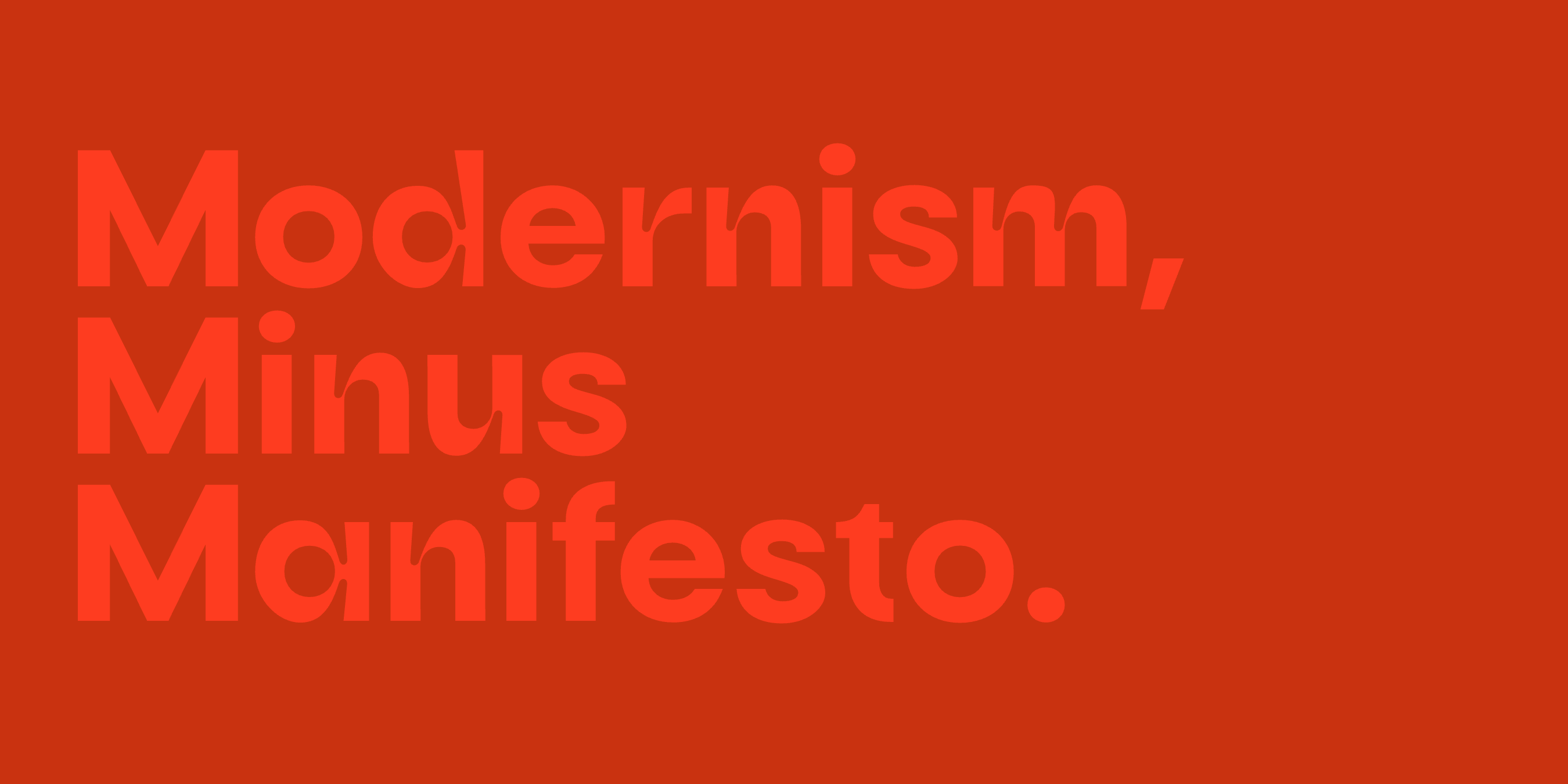
Moderne Typografie: Was sie 2026 wirklich bedeutet
Moderne Typografie ist einer dieser Begriffe, unter denen jeder Designer etwas anderes versteht. Für die einen sind es geometrische Sans-Serifs in Schweizer Tradition. Für andere die kontrastreichen Didonen aus Modemagazinen. Für wieder andere alles, was in den letzten zwölf Monaten erschienen ist. Nichts davon ist falsch, aber nichts davon ist vollständig.
Was Designer 2026 meist mit „modern“ meinen, ist Schrift, die in allen Kontexten funktioniert, in denen Marken heute bestehen müssen. Verpackungen, die für Instagram fotografiert werden, Produktseiten, durch die man auf dem Handy scrollt, Plakatwände, die man mit 100 km/h passiert, App-Oberflächen, auf die man eine halbe Sekunde schaut. Die Formen, die an all diesen Orten funktionieren, haben einige Merkmale gemeinsam.
Wie moderne Typografie in der Praxis aussieht
Erstens sind moderne Schriften auch in kleinen Größen klar lesbar. Durch Smartphones und Produktoberflächen muss ein Markenauftritt bei 16px genauso oft funktionieren wie bei 200px. Der Mojomox-Katalog ist auf diese doppelte Größenordnung abgestimmt.
Zweitens zeigt moderne Schrift ihre Persönlichkeit über Alternativen und Stilsets statt über ausgefallene Buchstabenformen. Für flüchtige Betrachter liest sich die Überschrift wie eine normale Wortmarke, doch wer genauer hinschaut, sieht die bewussten Entscheidungen (ein weicheres ‚a‘, ein einstöckiges ‚g‘, ein ungewöhnliches ‚R‘).
Drittens kommen moderne Familien mit vollständigen Schnitten und variablen Versionen. Ein einzelner Schnitt ist ein einzelnes Werkzeug. Eine Familie mit neun Schnitten und variabler Interpolation ist ein System.
Sieben Mojomox-Schriften, die für moderne Typografie heute stehen
Vole
Geometrische Sans-Serif mit fließenden Punzen. Die Punzen fließen auf eine Art, wie es bei den meisten geometrischen Grotesks nicht der Fall ist, und dadurch wirkt Vole freundlich und modern zugleich. Eine klare, moderne Wahl für technikaffine Konsummarken.
Moderne Sans-Serif mit weichen Innenecken. Die geometrische Basis hält sie diszipliniert, die weichen Ecken machen sie menschlich. Gut überall dort, wo Moderne nicht kühl wirken soll.
Kräftige organische Serifenschrift. Der Bauhaus-Gedanke, verfeinert für 2026. Hochwertig, ohne gekünstelt zu sein, warm, ohne weich zu sein.
Moderne Serifenschrift mit eleganten Proportionen. Selbstbewusste Striche, die sich nicht in den Vordergrund drängen. Die Serifenschrift der Wahl, wenn eine Marke moderne Eleganz ohne Drama will.
Moderne, elegante Sans-Serif mit Kontrast. Der Kontrast verweist auf klassische Editorial-Arbeit, die humanistische Basis hält sie aktuell.
Moderne architektonische Grotesk mit angeschnittenen Diagonalen. Ein feines konstruktives Detail, das erst auf den zweiten Blick auffällt. Eine durchdachte Wahl für designorientierte Marken.
Scharfe, schmale Serifenschrift mit langen Endstrichen. Die italienische Editorial-Tradition, umgesetzt mit heutigen Proportionen und heutiger technischer Präzision.